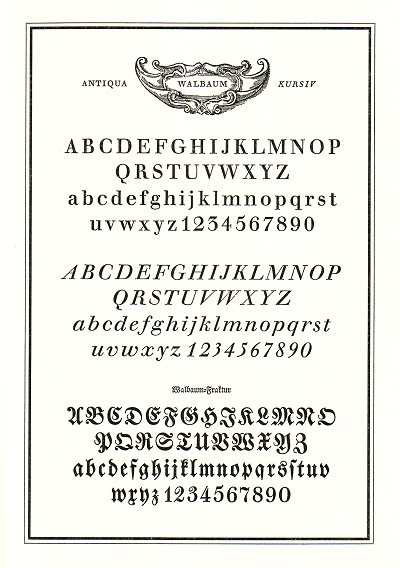
Tipos de Walbaum
A Walbaum será a mais humanista de todas as letras classicistas. De facto, apesar do rigor e da austeridade do desenho típico desta época imperial, napoleónica e despótica, esta variante alemã tem um desenho algo mais burguês e moderado, algo menos aristocrata e imperial que a ríspida letra do clã dos Didots e de Giambattista Bodoni. Entre as edições mais recentes, realço a da fundição Storm Foundry www.stormtype.com |